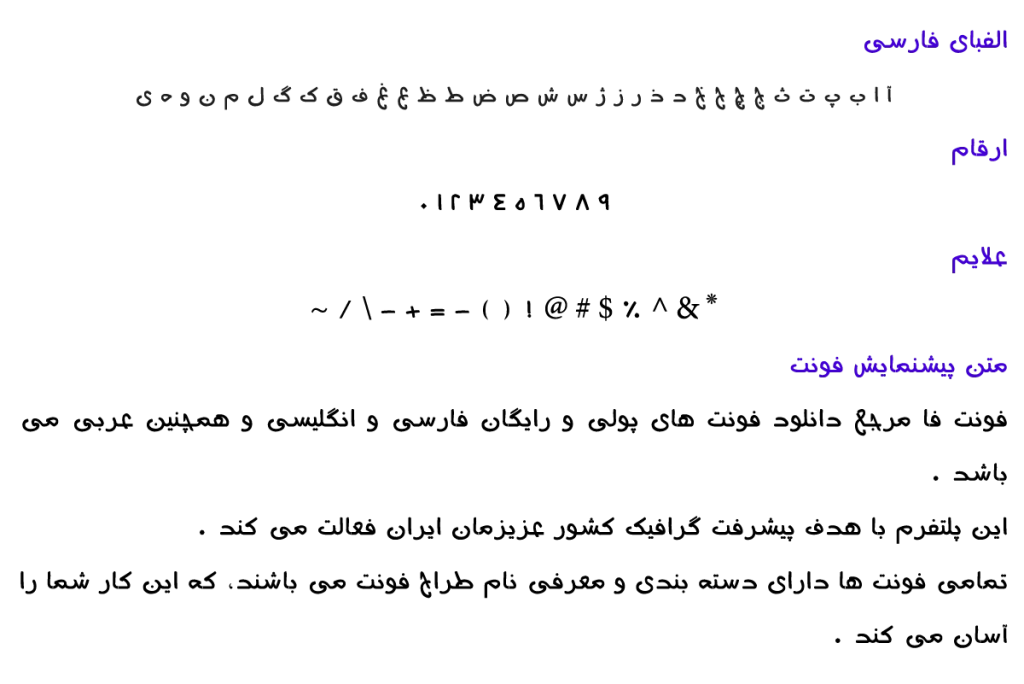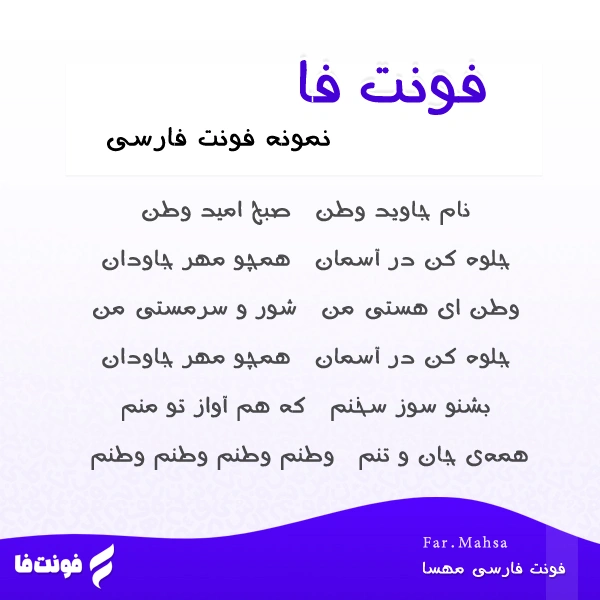
فونت فارسی مهسا – Far Mahsa
طراح فونت: ابوالفضل سيل سپور نوع فونت: فونت دست نویس
پیشنمایش فونت مهسا
توضیحات و معرفی فونت مهسا
فونت فارسی مهسا ( Far Mahsa ) از مجموعه فونت های سری Far می باشد، همچنین نوع فونت دست نویس می باشد.
فونت فوق العاده زیبای معرفی شده توسط ابوالفضل سيل سپور در سال 1390 طراحی و ساخته شده است.
همچنین فونت Far Mahsa در یک وزن معمولی است.
نگاهی بیندازید به تصویر زیر که نمونهای از این تایپ فیس را در شعر «وطن» نمایش می دهد.